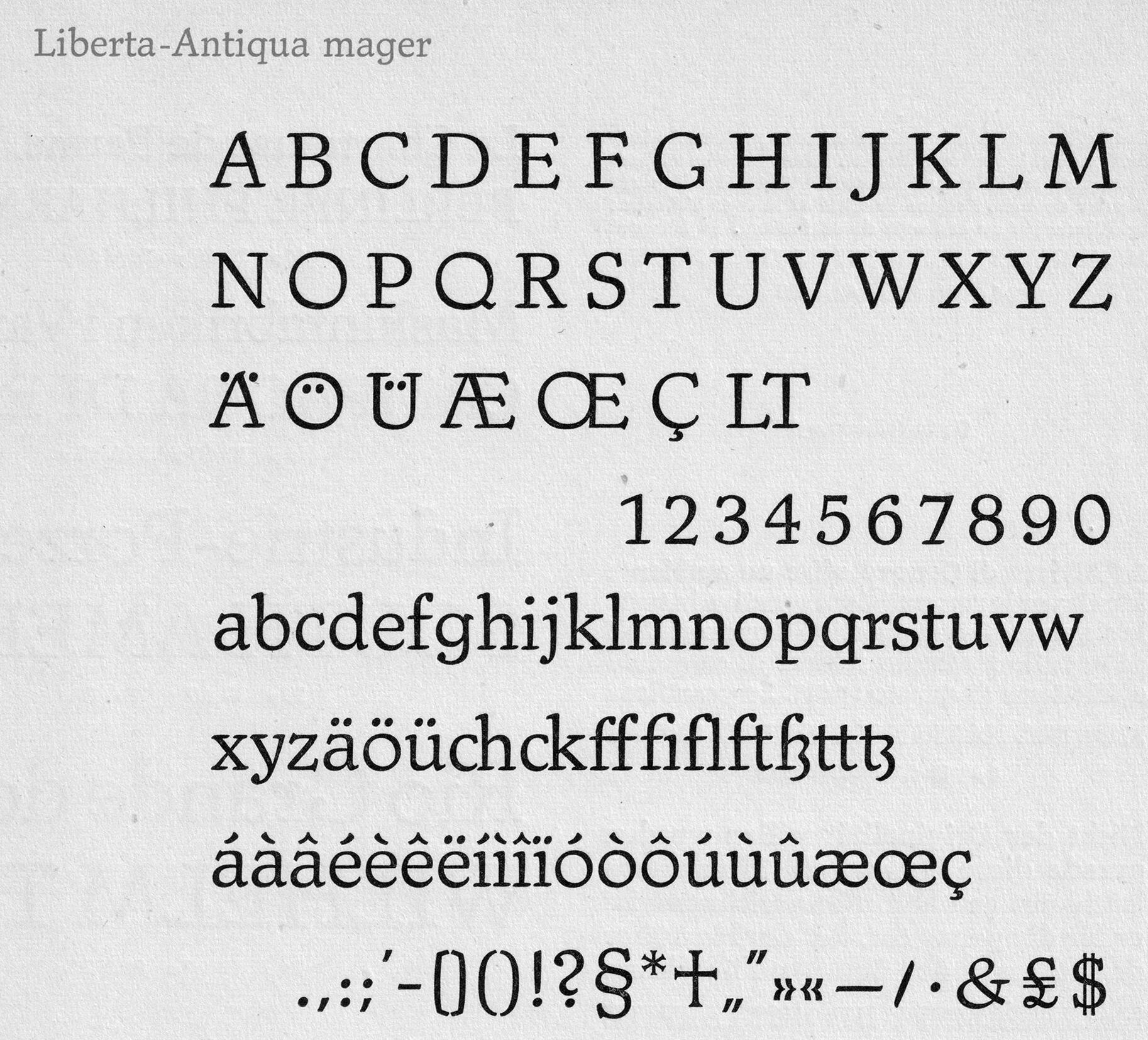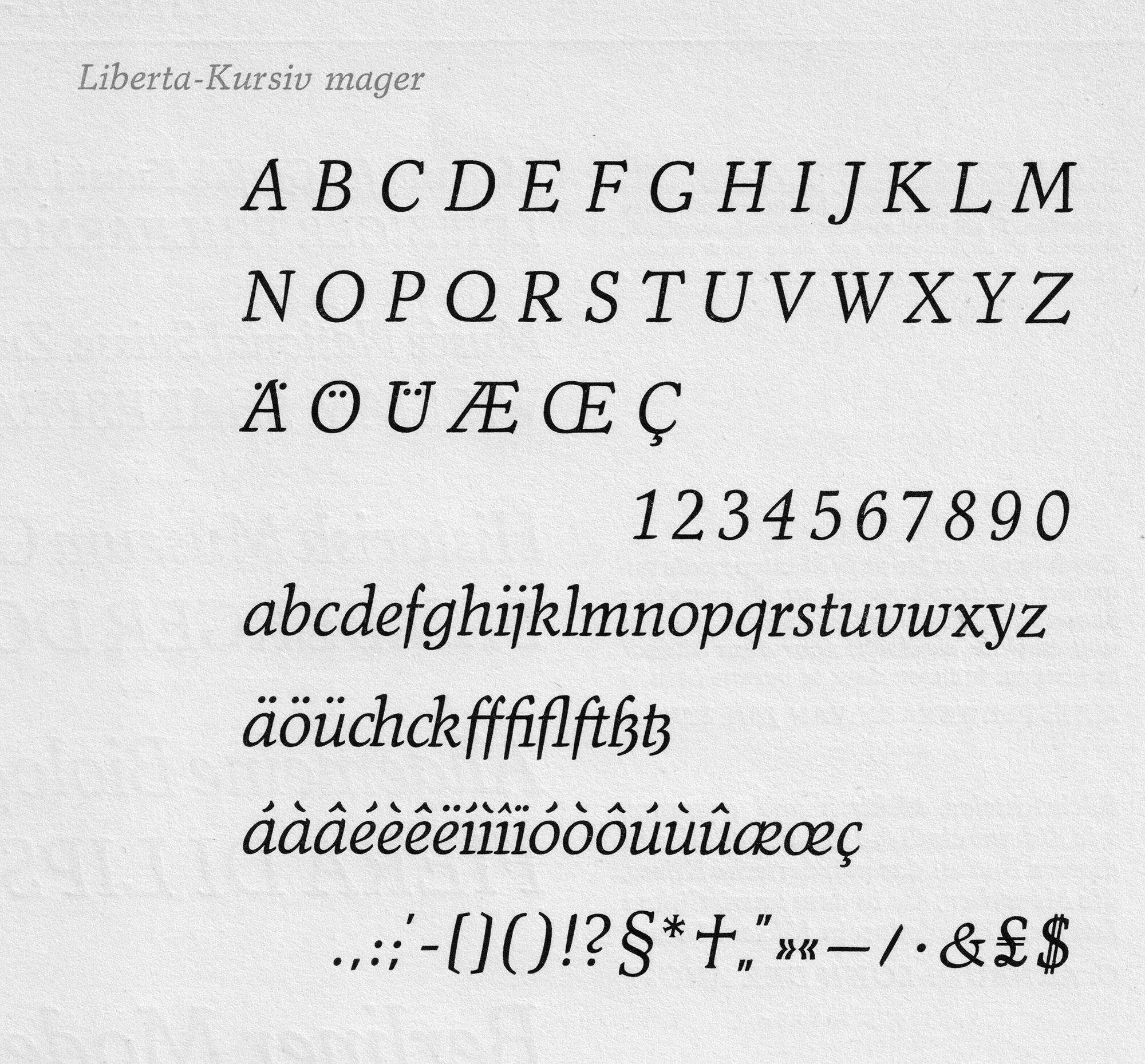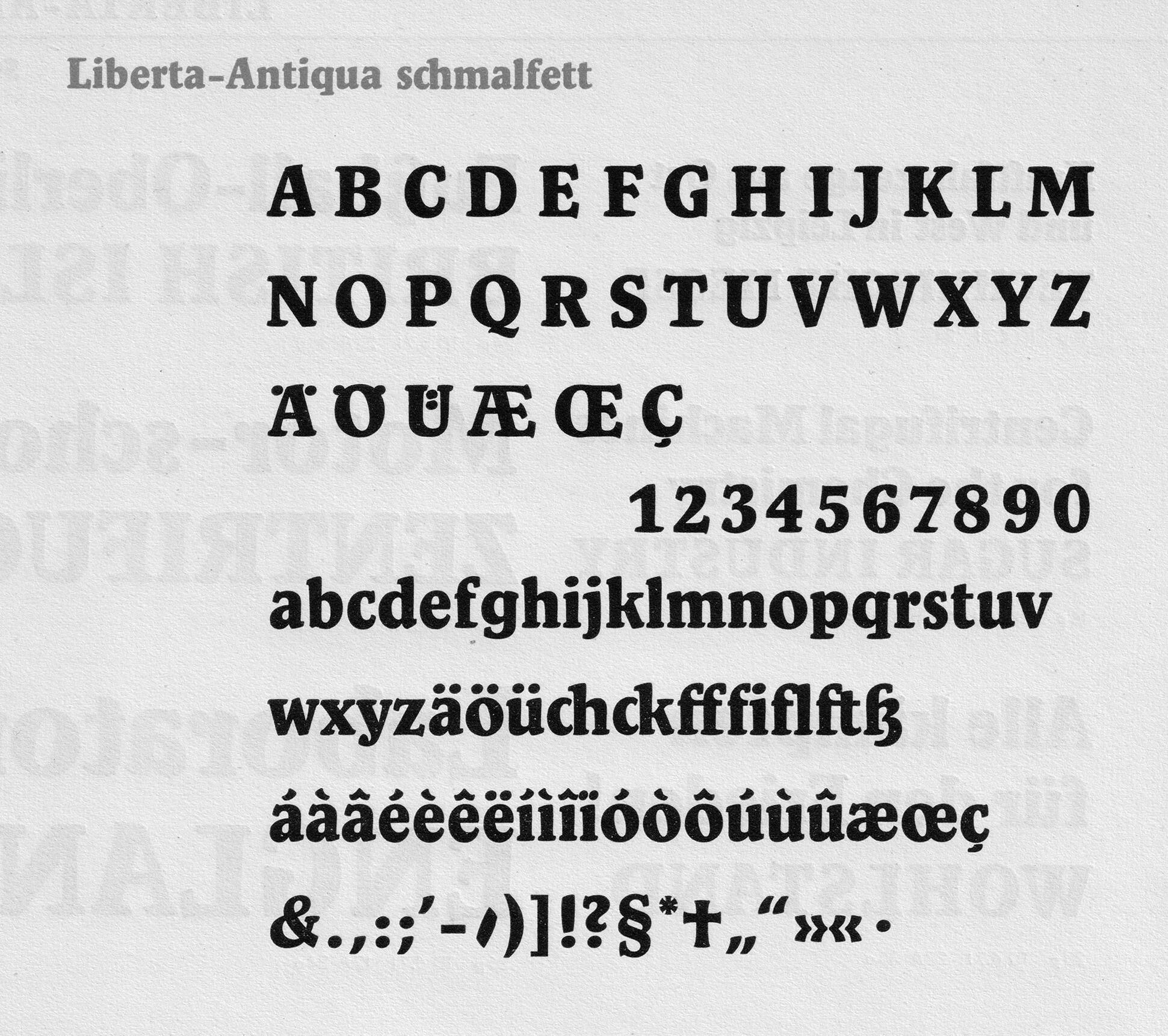
Daten zur Schrift
Herbert Thannhaeuser
Foundry: Typoart
erschienen: 1956
Art: serif
Formprinzip: Antiqua humanistisch
Die Liberta von Herbert Thannhaeuser erschien 1956 bei Typoart. In digitaler Form ist die komplette Familie bislang nicht verfügbar. Elser + Flake bietet zwei Schnitte an und unter dem Namen Trybuna gibt es Digitalisierung von RMU in drei Schnitten.
Eine sehr freie Interpretation, die jedoch ausdrücklich auf die Liberta als Quelle verweist, ist die Dederon Serif der Suitcase Type Foundry. Die Kontour von Sibylle Hagmann beruht ebenfalls auf der Liberta, ohne dabei eine reine Digitalisierung zu sein.